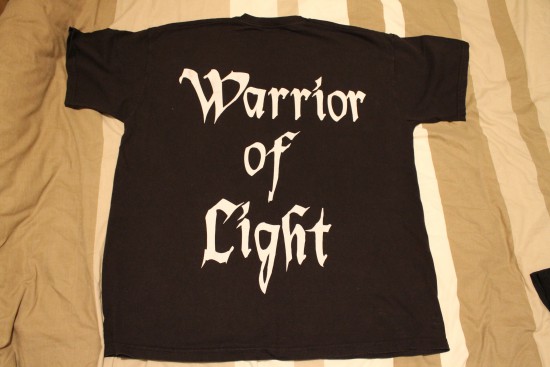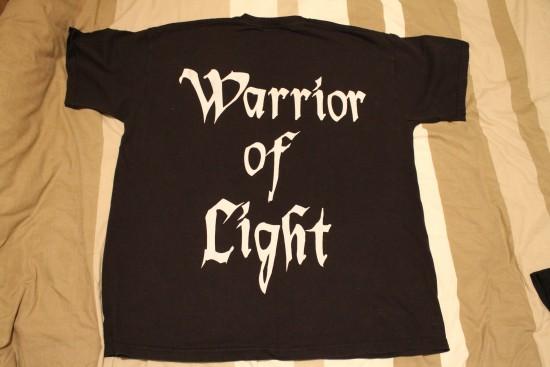
Kennt jemand diese Schrift?
bin verzweifelt auf der Suche nach der Schriftart die auf dem Bild zu sehen ist.
Kann jemand helfen?
Wenn es nicht unbedingt genau diese sein muss, würde ich bei dafont schauen, da gibt es bei Gothic>Medieval ausreichend ähnliche. Evtl. die "Lotharus" in die Breite gezogen …
Ideal wäre natürlich wenn jemand genau diese Schriftart kennen würde...